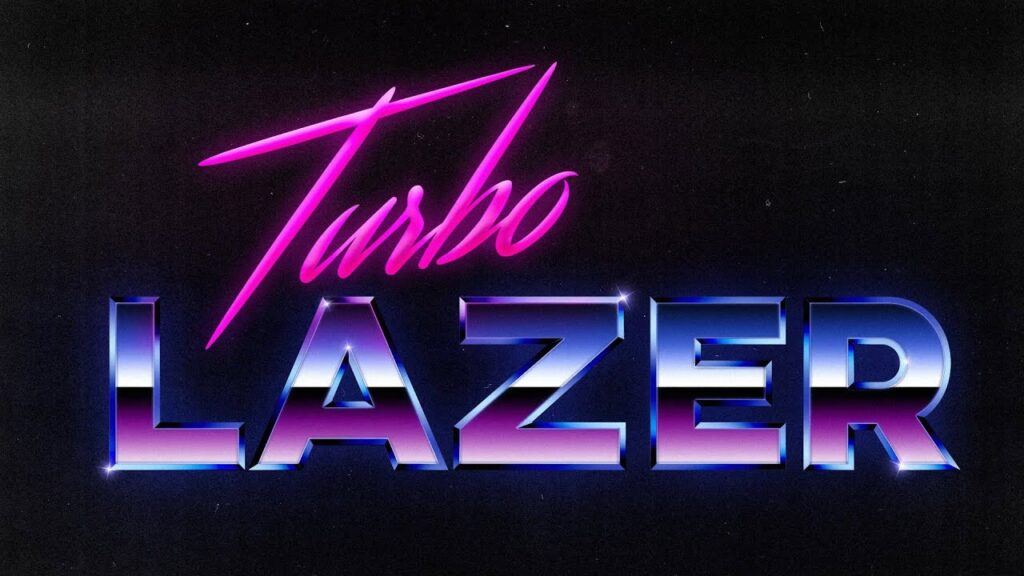
80'erne var et årti præget af dristighed, farver og en helt unik visuel stil. Fra mode til musik og film afspejlede designet en tid med optimisme og teknologisk fremgang. Denne æra har haft en vedvarende indflydelse på design og fotografi, og mange søger i dag at genskabe det karakteristiske 80'er-look i deres egne kreative projekter. To nøgleelementer i at fange denne æstetik er valget af de rigtige skrifttyper og anvendelsen af specifikke fotoeffekter. Lad os dykke ned i, hvordan du kan bringe 80'ernes magi til live i dit arbejde.
For at forstå 80'ernes visuelle identitet er det vigtigt at se på de skrifttyper, der var fremherskende. Mange af disse skrifttyper havde rødder i tidligere årtier, men oplevede en genoplivning eller blev brugt på nye, iøjnefaldende måder i 80'erne. De spændte fra elegante, art deco-inspirerede designs til dristige, geometriske og futuristiske skrifter.
Ikoniske Skrifttyper fra 80'erne
Når man tænker på 80'ernes skrifttyper, kommer man ofte til at tænke på titelsekvenser fra populære film og tv-serier eller albumcovers fra tidens musikikoner. En af de mest genkendelige er den, der blev brugt til titlen på den populære serie Miami Vice. Denne skrifttype kaldes Broadway. Selvom den ofte associeres med 80'erne, har den faktisk en meget stærk art deco-æstetik, der stammer fra en tidligere periode. Desværre er Broadway ikke en gratis skrifttype. Hvis du leder efter et fremragende gratis alternativ, der fanger den samme stemning, er Limelight et rigtig godt bud.
Et andet mindeværdigt eksempel er skrifttypen brugt på Prince's album Purple Rain. Det er usikkert, om dette var en eksisterende skrifttype eller om den blev designet specifikt til albummet. Uanset hvad, findes der alternativer, der kommer tæt på. Still Time er en skrifttype, der ligner en del. En anden skrifttype, der er lidt anderledes, men i samme stil, er Colors of Autumn.
Der er også skrifttyper, som mange sandsynligvis vil genkende fra film om forretning og lignende temaer. En gratis version af en sådan skrifttype kaldes Six Caps. Disse skrifttyper har ofte et mere formelt eller 'corporate' præg, men stadig med et tidstypisk snit.
Udover de mere nicheprægede skrifttyper var der også nogle meget udbredte og berømte skrifttyper, der var overalt i 80'erne og som faktisk aldrig rigtig forsvandt igen. Blandt disse finder vi Helvetica, som man for eksempel ofte fandt på Lego-æsker. Andre inkluderer Futura og Avant Garde, hvor sidstnævnte minder en del om Futura. Disse er nogle af de mest berømte skrifttyper, der eksisterer. Desværre er de ophavsretligt beskyttede, og det tætteste man kan komme på at få dem gratis er at finde 'knockoffs' eller efterligninger. Disse efterligninger kan dog være ret tæt på originalerne. Det er værd at bemærke, at Helvetica faktisk er inkluderet i Mac OS X, og at Arial til en vis grad var baseret på denne skrifttype. Dette understreger, hvor indflydelsesrige disse designs har været.
Skab 80'ernes Fotoeffekt i Photoshop
Udover skrifttyperne spillede selve billedernes æstetik en stor rolle i 80'erne. Tænk på farver, lys og teksturer. At genskabe dette look i digital form kræver specifikke teknikker i billedredigeringsprogrammer som Photoshop. Her er en trin-for-trin guide til, hvordan du kan give dine fotos en retro 80'er-effekt.
Start med at åbne dit billede i Photoshop. Du kan bruge ethvert foto, du ønsker at give en retro-effekt. I denne guide tager vi udgangspunkt i et standardbillede. Åbn billedet ved at vælge Filer > Åbn (Ctrl/Kommando + O) og find billedet på din computer.
Det første skridt er at justere billedets toner og farver på en måde, der er karakteristisk for 80'erne. Dette gøres effektivt ved hjælp af et Justeringslag for Kurver.
Trin 1: Tilføj et Justeringslag for Kurver
Nederst i Lag-panelet skal du klikke på ikonet "Opret et nyt fyld- eller justeringslag" (det ligner en cirkel, der er halvt fyldt med grå og halvt med hvid). Vælg derefter Kurver i menuen, der vises.
I Justeringer-panelet skal du ændre dropdown-menuen til den Røde kanal og modificere kurven ved at klikke og trække i den. Formålet er at skabe et farveskift, der emulerer den måde, film fra 80'erne gengav farver på, ofte med en tendens mod magenta eller cyan i skygger og højlys.
Skift derefter til den Grønne kanal og juster kurven på samme måde. Dette trin vil yderligere forme farvebalancen og bidrage til det specifikke 80'er-farveskema.
Til sidst skal du skifte til den Blå kanal og ændre kurven igen. Justering af den blå kanal er afgørende for at tilføje de kølige eller varme toner, der var populære i årtiet, og for at skabe kontrast i farverne.
Vores arbejde begynder at se godt ud, og vi er kun lige begyndt. Lad os fortsætte.
Trin 2: Tilføj et Justeringslag for Forløbskort (Gradient Map)
Nu tilføjer vi endnu et justeringslag: et Justeringslag for Forløbskort (Gradient Map).
Klik igen på ikonet "Opret et nyt fyld- eller justeringslag" nederst i Lag-panelet, men vælg denne gang Forløbskort.
I Justeringer-panelet skal du klikke på forløbet for at åbne Forløbsredigeringsprogrammet. I Forløbsredigeringsprogrammet skal du ændre farverne på forløbet. Formålet her er at 'mappe' bestemte farver til billedets lyseste og mørkeste områder, hvilket kan give en stærk, stiliseret farveeffekt, der var almindelig i 80'ernes grafik og billeder. Vælg farver, der passer til den ønskede 80'er-palette, ofte med kontrasterende farver i skygger og højlys.